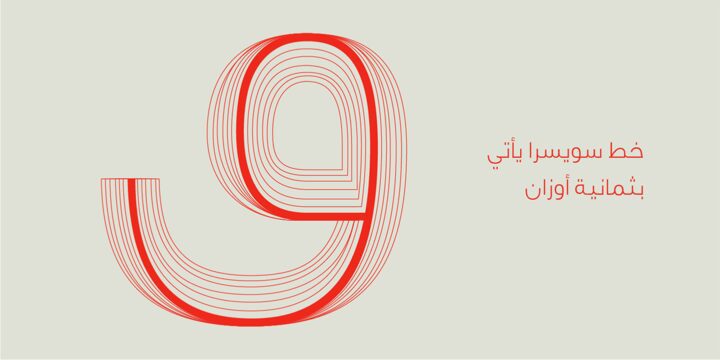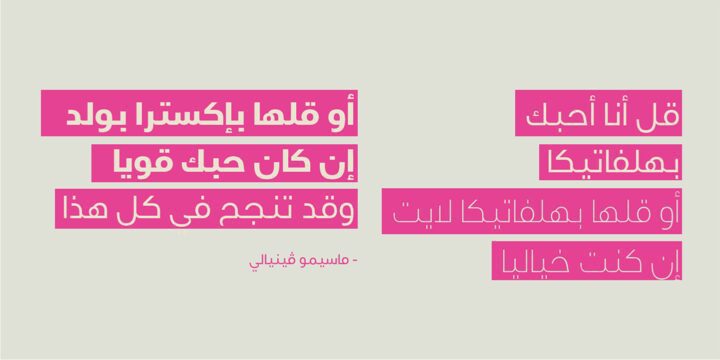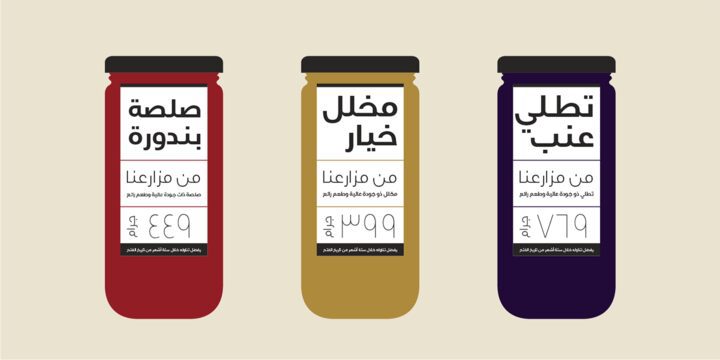
تتراوح أسعار الأوزان الفردية من $31.25 إلى $35.00، بينما تتوفر الحزمة الكاملة التي تضم جميع الأوزان بسعر $250.00. يُعد خط Swissra خيارًا مثاليًا للمصممين الذين يبحثون عن خط عربي يجمع بين البساطة والحداثة، مع مرونة في الاستخدام عبر مختلف التطبيقات